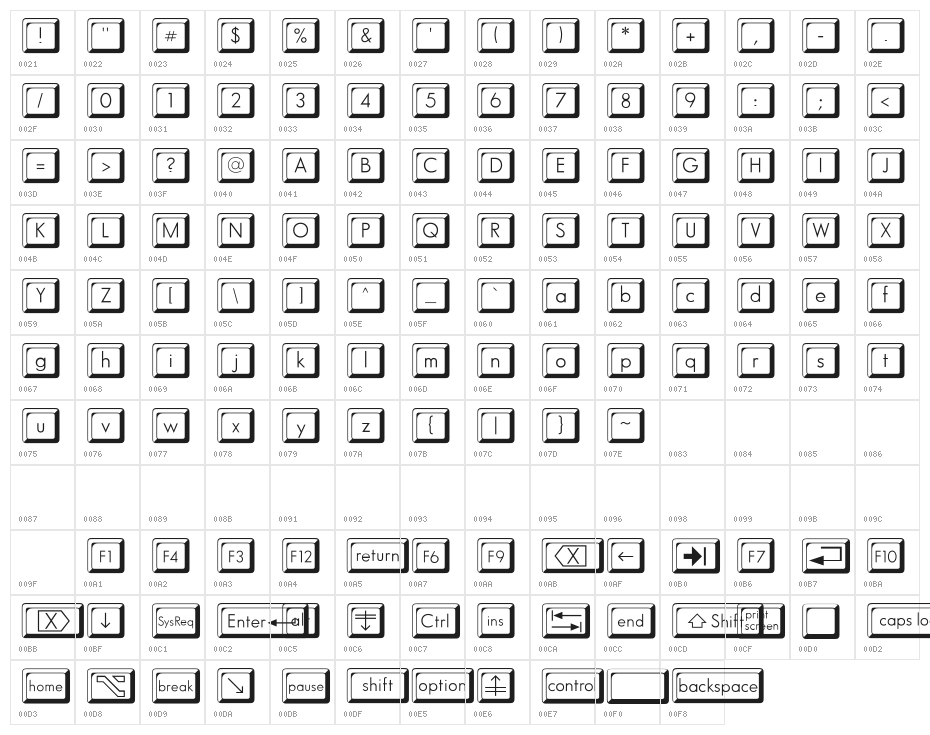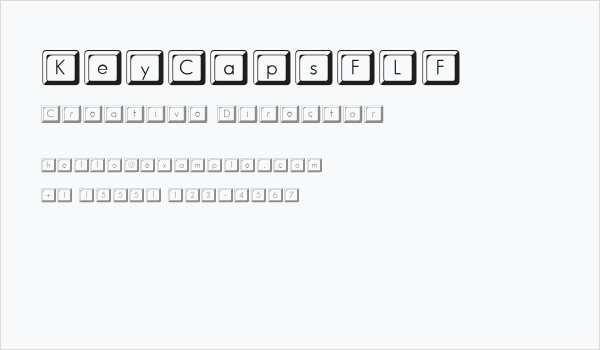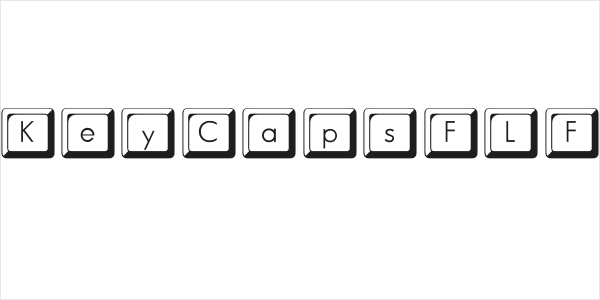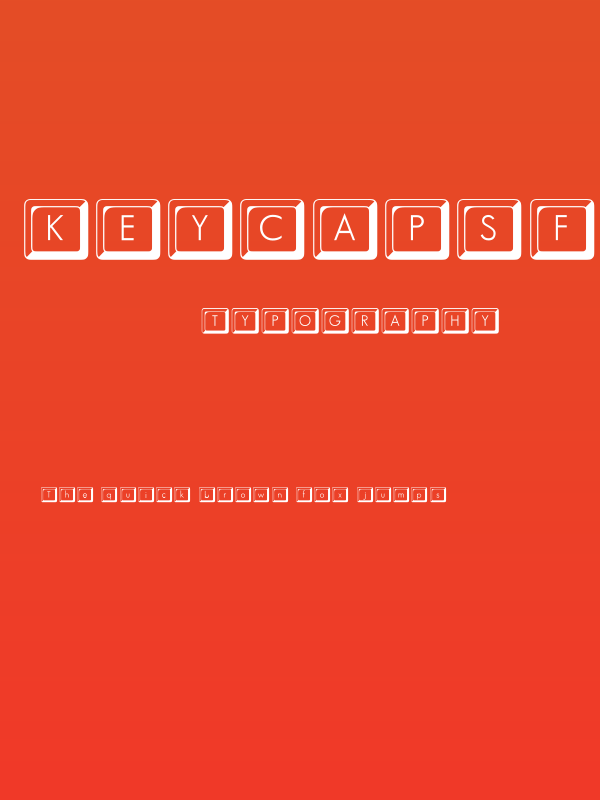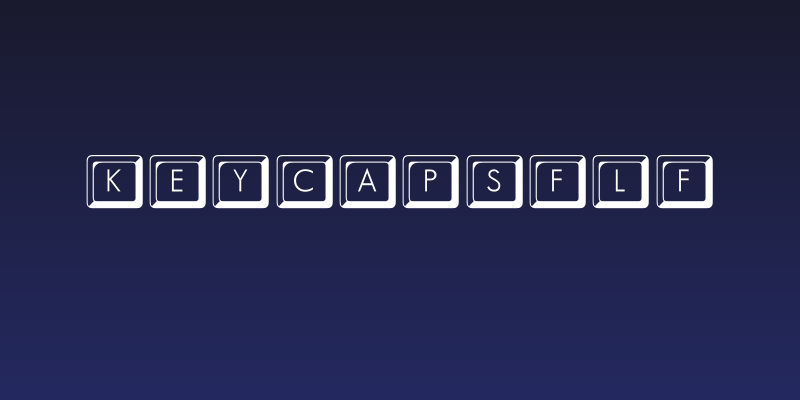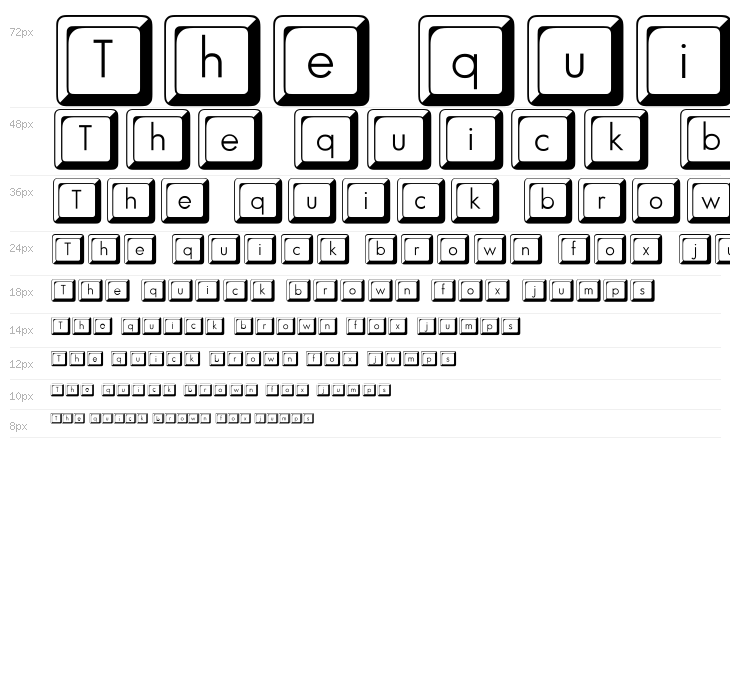
KeyCapsFLF Font
| 分类 | Typewriter |
| 整体风格 | Retro, Tech-inspired |
| 使用场景 | Logos, Headlines, Digital interfaces |
| 推荐项目 | Ideal for retro-themed designs, tech-related branding, digital interfaces, and educational materials. |